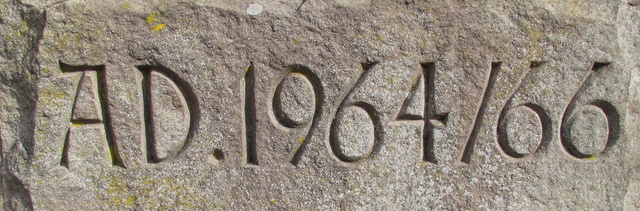
Inschrift in Sandstein
Suche den Schriftnamen dieser von einem Steinmetz in den 1960ern Jahren in einen Sandsteinquader eines Kirchbaues gehauenen Inschrift.
Das ist Handarbeit, vielleicht nach irgendeiner Vorlage, die aber sicher auch noch modifiziert wurde. Das antikisierende A paßt zum Beispiel nicht so recht zu den (damals) modernen Ziffern. Es würde mich sehr wundern, wenn man diese Zeichen auf eine konkret zu benennende Schrift zurückführen könnte.